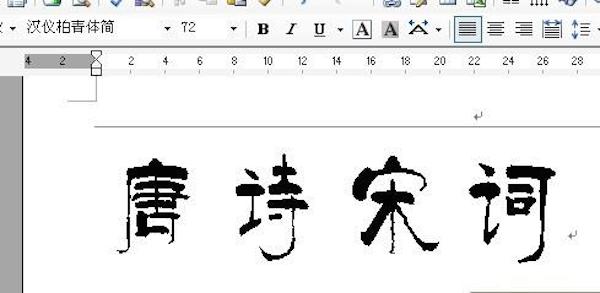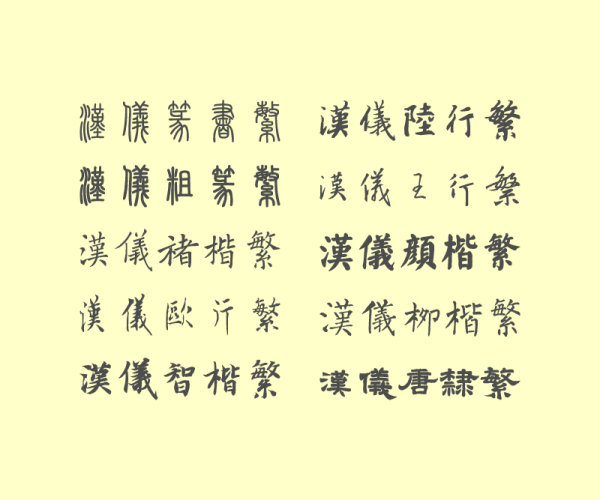
軟件介紹 軟件標(biāo)簽: 漢儀字體 字體打包 漢儀字體Mac版蘋果電腦Mac os平臺上的一款mac字體,這個字體非常的經(jīng)典,在photoshop相關(guān)的平面設(shè)計設(shè)計軟件,一般的瀏覽器,閱讀器,辦公學(xué)習(xí)中都經(jīng)常能用的到該字體。本站提供了所有可以在蘋果電腦上使用的漢儀字體字體,需要的朋友們可以前來下載使用。基本簡介實用性較強,比已有的行楷行書味足,顯得更加活潑,筆畫較為粗壯。整副字既嚴(yán)肅又不呆板,流暢大方、雅俗共賞。字體安裝方法:蘋果電腦MAC系統(tǒng)字體安裝教程:點擊查看 本字體如果商用,請聯(lián)系漢儀字體官方獲得授權(quán)。 軟件截圖 上一張下一張(1 / 1) 安裝詳細(xì)截圖 猜你喜歡 字體庫 漢儀字體 字體庫 字體庫是包含超多字體的軟件,里面有非常多的字體,一個軟件就能解決很多問題,不用再一個個字體去下載了,下載一個軟件即可擁有超多種字體,是十分好用的字體包工具。 查看更多>> 字加(字體管理) 8.04M/中文/6.0/v0.9.9.15 免費版下載 字體超市管家 62.50M/中文/8.7/v1.6.0.0 官方版下載 常用字體庫 21.50M/中文/8.0/最新版下載 ifonts字體助手官方版 57.79M/中文/5.0/v2.4.0 最新版下載 wps字體庫打包 216.00M/中文/7.2/77款下載 鏈圖云字體助手 71.50M/中文/10.0/v3.0.6 電腦版下載 漢儀字體 漢儀字體有哪些?漢儀字體下載大全收錄了所有好看的、經(jīng)典的漢儀字體合集,漢儀字體是由北京漢儀科印信息技術(shù)有限公司創(chuàng)作,這些字體種類齊全,各具特色、應(yīng)用領(lǐng)域廣泛,喜歡漢儀字體的朋友歡迎來綠色資源網(wǎng)免費下載使用! 查看更多>> 阿里巴巴普惠字體 26.00M/中文/0.8/官方ttf版下載 漢儀天宇風(fēng)行體 21.41M/中文/5.0/下載 漢儀蘇澤立行楷精修版簡 3.01M/中文/4.0/免費版下載 漢儀正圓(共7款) 17.96M/中文/2.8/ttf免費版下載 漢儀可愛字體打包 41.20M/中文/5.0/14款下載 漢儀曉波花月圓字體 1.89M/中文/0.0/下載 其他版本下載 標(biāo)題 大小 更新日期 下載 下載地址 電腦版 漢儀字體打包大全 for Mac 蘋果電腦版_ 共131款字體 點擊報錯 軟件無法下載或下載后無法使用,請點擊報錯,謝謝! 關(guān)閉報錯反饋 請描述您所遇到的錯誤,我們將盡快予以修正,謝謝! *必填項,請輸入內(nèi)容 本類最新 漢儀孟瑞體ttf v1.0 官方版 漢儀字庫免費 132款 阿里巴巴普惠字體 官方ttf版 漢儀字體打包大全 for Mac 蘋果電腦版_ 共131款字體 漢儀純愛情書拼音體 ttf版 漢儀北魏寫經(jīng)w字體 免費版 相關(guān)文章 Photoshop字體安裝使用方法和技巧 如何調(diào)網(wǎng)頁字體大?。?/a> 改變文章字體大小/背景顏色(含cookie控制) 提高用戶體驗:網(wǎng)頁字體大小的設(shè)計 調(diào)節(jié)瀏覽器的字體大小 電腦字體大小的改變設(shè)置 用戶評論 熱門評論 最新評論 發(fā)表評論 查看所有評論(0) 昵稱: 請不要評論無意義或臟話,我們所有評論會有人工審核. 字?jǐn)?shù): 0/500 (您的評論需要經(jīng)過審核才能顯示)